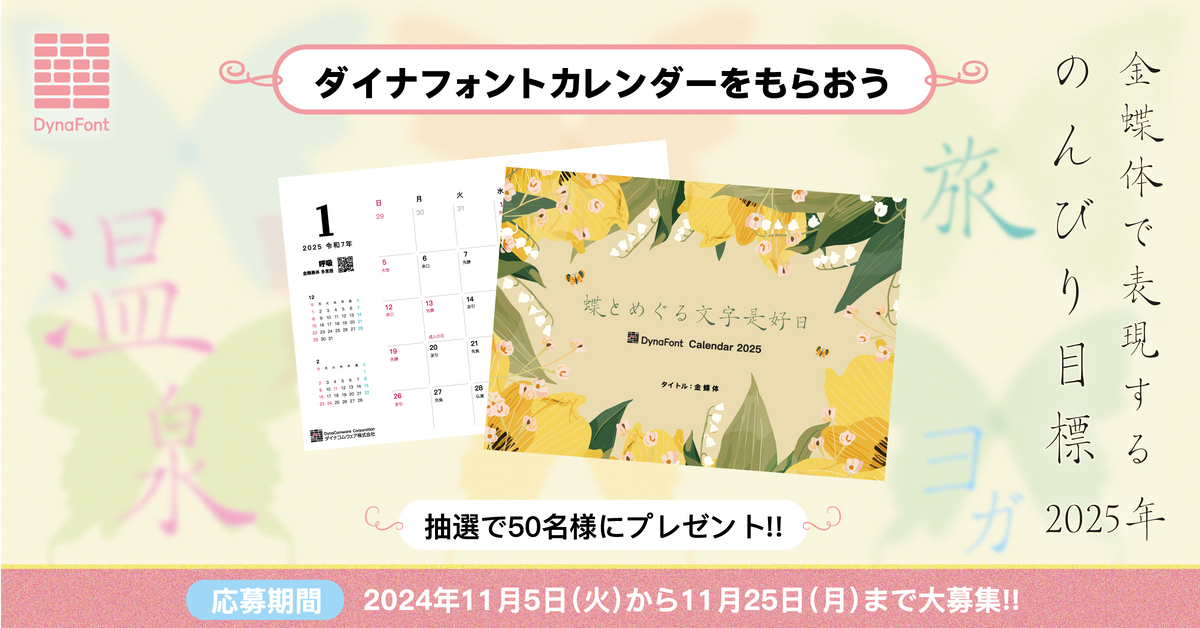
2024年グッドデザイン賞「金蝶体」受賞記念キャンペーン「金蝶体で表現する“2025年のんびり目標”を11/25まで大募集!」が開催。抽選で50名に「ダイナフォント2025年カレンダー」プレゼント
ダイナコムウェアは、詩情のある空間を作り出し緩慢な生命の本質を取り戻す文字「金蝶体」の2024年グッドデザイン賞受賞を記念して「金蝶体」で表現する“2025年のんびり目標”を2024年11月5日(火)~11月25日(月)までの期間、募集。
参加者から抽選で50名に、ダイナフォント2024年新書体「金蝶体」などを盛り込んだ12書体で12の暦を詩的に表現したダイナフォント2025年カレンダー「蝶とめぐる文字是好日」をプレゼントする。
参加者でダイナフォント2025年カレンダーが当選者にはに、自身の「金蝶体で表現する2025年のんびり目標」を画像にして応募したメールアドレスに送付もされる。
ダイナフォント2025年カレンダー「蝶とめぐる文字是好日」
ダイナフォント2025年カレンダー「蝶とめぐる文字是好日」は、2025年の毎日が穏やかで好い日であることに願いを込めて制作。
願いにピッタリなタイトルとして詩情と安らぎに溢れたダイナフォント2024年新書体「金蝶体」を使用している。
12の暦のイラストにはそれぞれ“蝶”が隠れている。
その他にも2024年の新書体からは秋に登場したばかりのダイナフォント新書体である「POPミックスA」や「京劇体A」なども登場。
機能面では12の暦に使用した書体を更に詳しく知ることができるそれぞれのWebページへと誘われるQRコードや、記入スペースの確保、当月の前後1ヶ月および六曜の表記、読み心地を追求したダイナコムウェアフラッグシップフォント「金剛黒体」をベースにした作成により、毎日の生活の中で快適にご使用いただけるカレンダーになっている。
2024年グッドデザイン賞受賞書体「金蝶体」
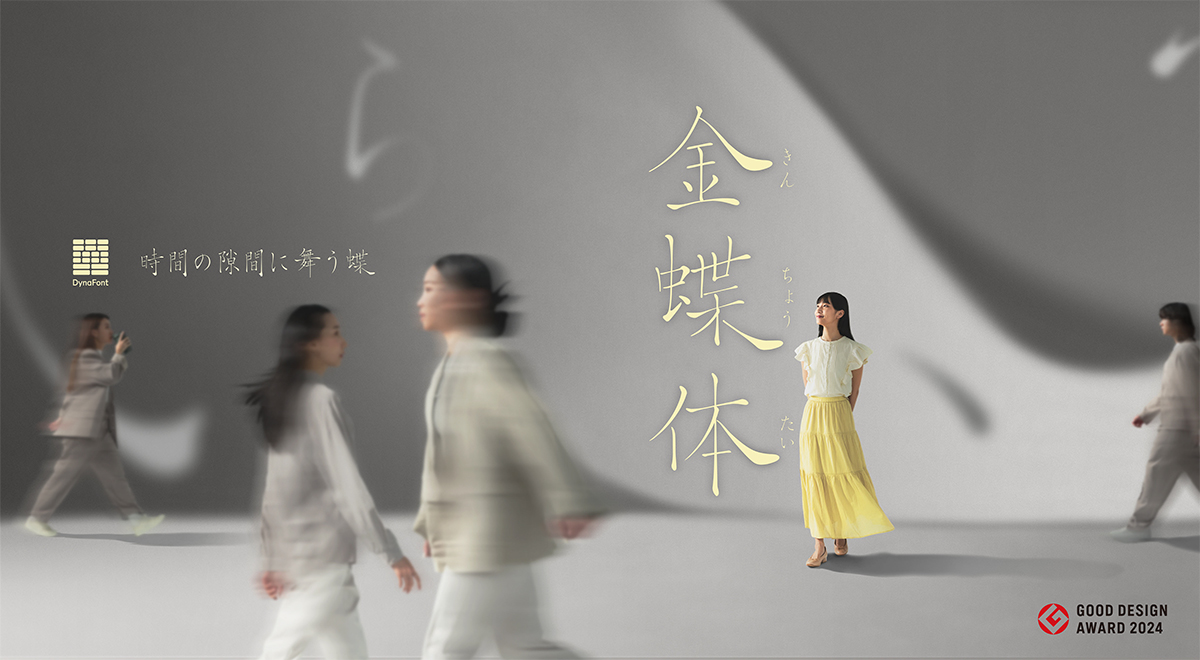
「金蝶体」は台湾の高名な詩人である周夢蝶氏の小楷書道から着想を得て、手書きの慎重さとぬくもりをそのままに “蝶” をコンセプトとして、躍動する生命力を表現したダイナフォント2024年の新書体。
2024年2月に東京・池袋サンシャインシティで開催された印刷メディアビジネスの総合イベント「page2024」のダイナコムウェアブースでの情報解禁から、4月にダイナフォント2024年春の新書体として「金蝶体A」をリリース、10月16日に2024年グッドデザイン賞を受賞、10月17日にダイナフォント2024年秋の新書体として新デザインの欧文を収録したバージョン「金蝶体B」をリリースするなど、一年を通じて大きな話題を呼び、まさにダイナフォントの2024年を象徴する活躍を見せてくれた。